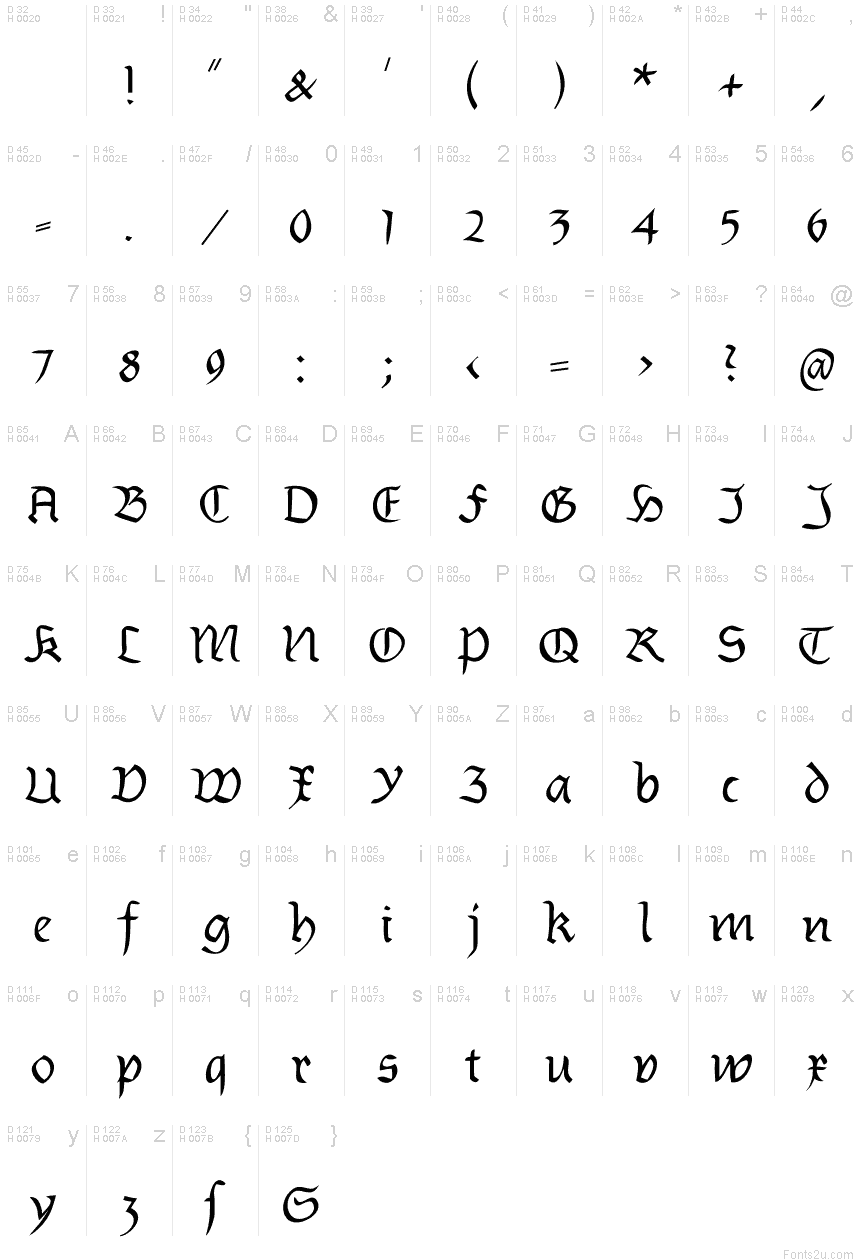
Burtinomatic od Mk to darmowy font w stylu retro blackletter z cudownie ekscentrycznym twistem. Atramentowe pociągnięcia przechodzą od ostrych, przypominających sztylety kątów po miękkie, zaokrąglone łuki, tworząc wygląd łączący średniowieczny skrypt z undergroundowym plakatem koncertowym. Litery skupiają się w gęstym, dramatycznym rytmie, dzięki czemu nawet krótkie słowo wygląda jak wyrazisty emblemat czy herb.
Używając Burtinomatic, nadasz tytułom na logotypach zespołów, okładkach książek fantasy, ekranach gier, gotyckich zinach, wzorach tatuaży czy szyldach barowych prawdziwie kultowy charakter. Ten darmowy font najlepiej sprawdza się w dużych rozmiarach, gdzie jego nietypowe krawędzie i masywne łuki mogą w pełni wybrzmieć; w tekście głównym połącz go z czystym, geometrycznym krojem bezszeryfowym, aby zachować czytelność, podczas gdy nagłówki skradną całą uwagę.